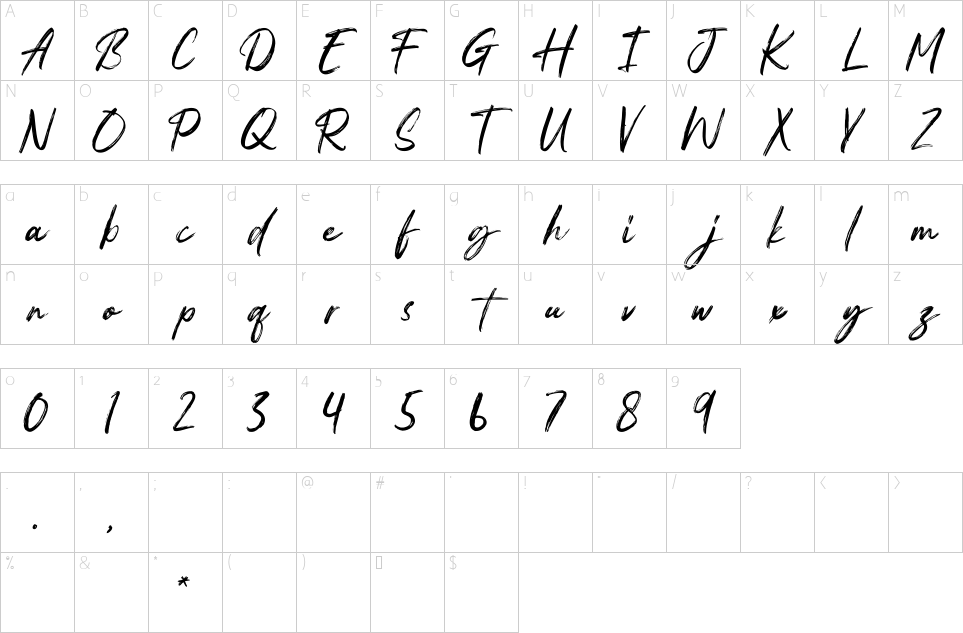
Averna En Rails Font – Download Grátis
A fonte ‘Averna En Rails’ é uma adição encantadora à sua coleção de fontes gratuitas, criada especialmente pelo Lettermine. Esta fonte é um dos novos lançamentos que promete agradar com seu design elegante e moderno. Ideal para os designers que buscam uma fonte para trabalhos digitais e gráficos, Averna En Rails oferece uma aparência atraente e única que se adequa perfeitamente a elementos como ícones e textos. Com o formato suportado tanto para Windows quanto para Mac, Averna En Rails é uma fonte versátil que deve estar em qualquer coletânea de recursos gráficos. Desde o seu lançamento, muitos designers a adotaram para suas criações, e agora você pode acessá-la gratuitamente. Download Averna En Rails para explorar sua capacidade única e adicionar um toque especial à sua próxima obra de arte digital.